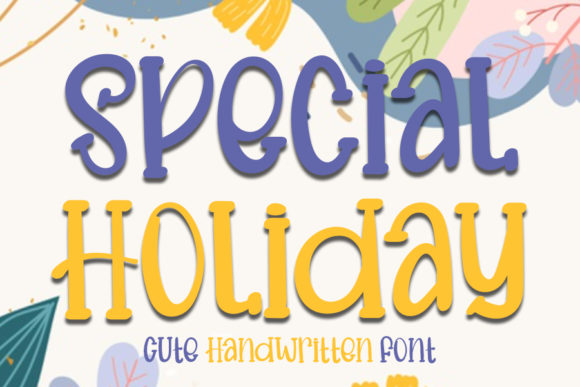
[Creativefabrica] Special Holiday Font
Special Holiday - это простой, круглый и симпатичный шрифт на дисплее.
Его гибкость и веселый дух скрасят каждый ваш дизайн.
Наслаждайтесь этим красивым шрифтом и изучайте его бесконечные вариации.